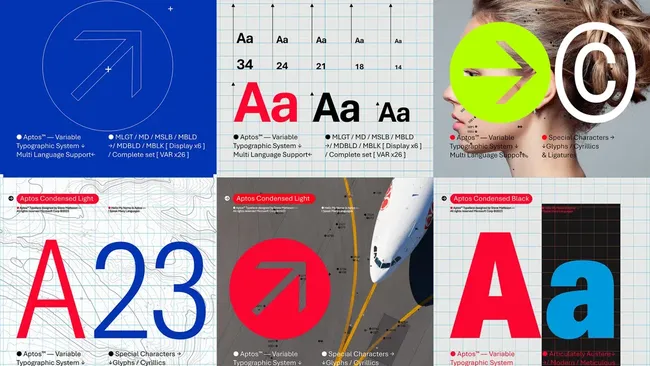
Bye Calibri, Halo Aptos! Microsoft Pamerkan Font Baru untuk Word, dkk
Bye Calibri, Halo Aptos! Microsoft Pamerkan Font Default Baru untuk Word, dkk Foto: Microsoft
Dua tahun yang lalu, Microsoft mengumumkan rencananya untuk menggantikan Calibri dengan typeface default baru untuk Word, Excel, dan kawan-kawan. Setelah menimbang lima kandidat, kini Microsoft menemukan font default terbarunya yaitu Aptos.
Microsoft tidak menjelaskan alasan spesifiknya menggantikan Calibri dengan font default baru setelah 15 tahun. Namun pengumuman mereka mengindikasikan bahwa Aptos dibuat untuk mendukung display dengan resolusi dan kepadatan yang lebih tinggi.
"Font ini harus memiliki ketajaman, keseragaman, dan bagus untuk berbagai jenis display," kata Microsoft dalam postingan blognya, seperti dikutip dari Insider, Senin (17/7/2023).
Microsoft mendeskripsikan Aptos sebagai font sans-serif yang berani dan memiliki profesionalisme, kemampuan beradaptasi, dan lebih jelas. Microsoft mengklaim desain font ini membuatnya lebih mudah dibaca, terutama teks berukuran kecil.
Sama seperti typeface San Fransisco buatan Apple, Aptos juga hadir dalam berbagai gaya, termasuk condensed, monospaced, dan versi serif.
Aptos diciptakan oleh desainer Steve Matteson yang sebelumnya menciptakan font Segoe. Microsoft pertama kali menggunakan font Segoe sebagai font default Windows di Windows Vista, dan masih mempertahankan font ini di Windows 11.
Meskipun Aptos akan menjadi font default baru, Calibri tetap akan di-pin di bagian atas menu font, bersama pendahulunya Times New Roman dan Arial. Calibri sendiri telah menjadi font default Office sejak diluncurkannya Office 2007.
Sementara itu, empat font lainnya yang tidak terpilih menjadi font default baru tetap akan tersedia di Microsoft Office. Empat kandidat yang tidak terpilih itu adalah Grandview, Seaford, Skeena, dan Tenorite.
Microsoft mengatakan sudah mulai menggulirkan Aptos untuk ratusan juta pengguna Word, Excel, Outlook, dan PowerPoint. Aptos akan menjadi font default untuk semua pengguna Microsoft Office dalam beberapa bulan mendatang.